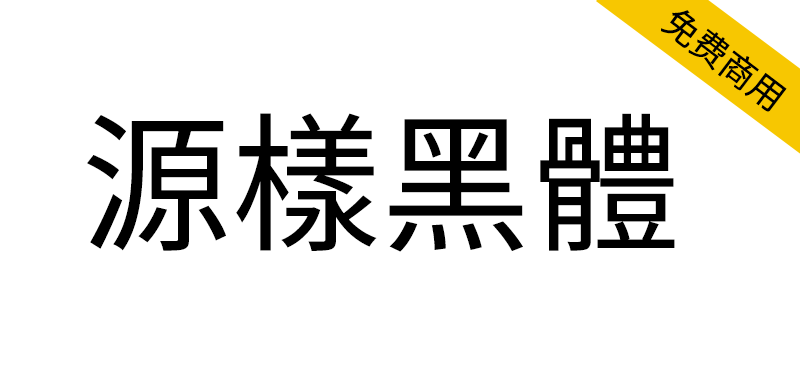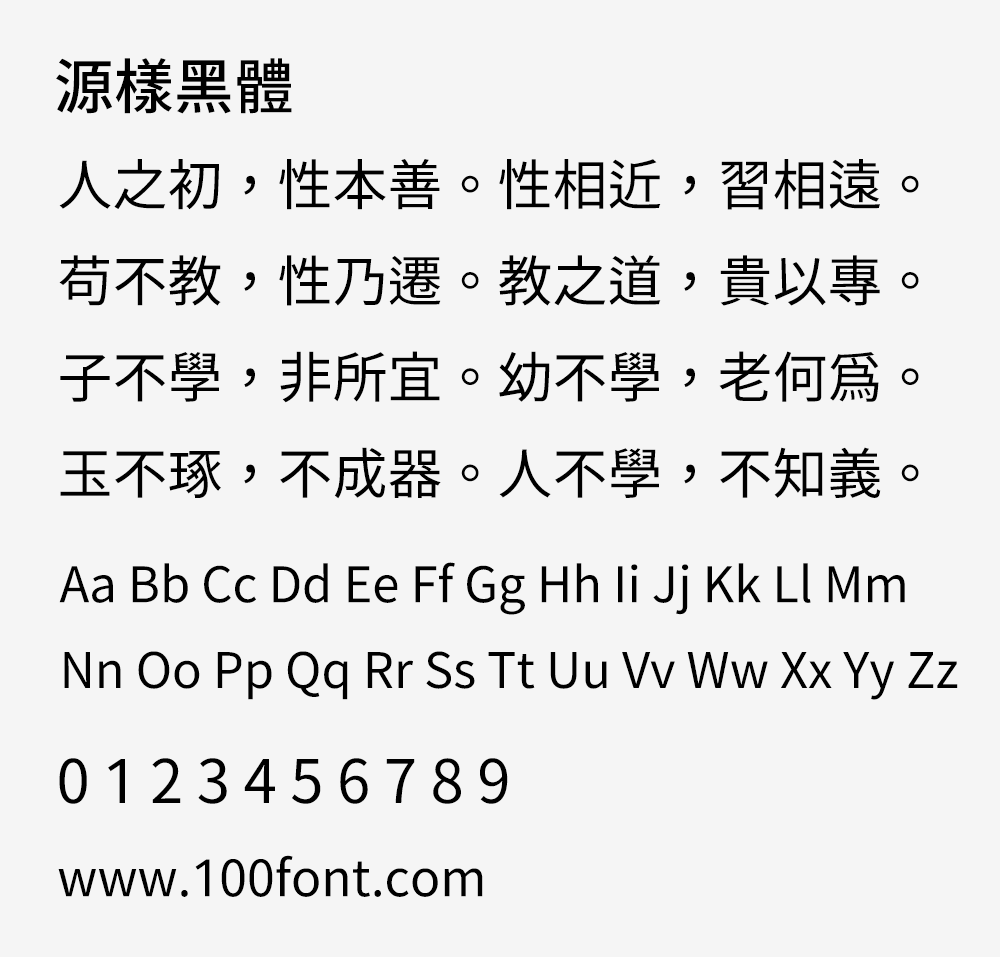
「源样黑体」是基于思源黑体的开放原始码中文字体。采用思源黑体韩文(KR)版本为主的字符,配合繁体中文惯用的置中标点,可排版传统印刷体风格的文件。
传统印刷体:思源黑体预设的台湾版本(TW)采用教育部标准字体,虽然适合教育用途,但不尽符合传统印刷体审美观。例如点、挑、撇笔画太多,文件排列时的的跳动感较大。源样黑体采用KR版本的字符为主,较接近传统印刷体习惯,排列感较为整齐。
源样黑体并没有造新的字符,所有字符都是来自思源黑体本身。所以KR版本未收录的罕用字或简体字,仍然会是TW、CN风格。
汉字不缺字:保留思源宋体所支持之所有汉字(包或日、韩文汉字与简体字),一般会用到的汉字几乎不会有缺字问题。同时也保留了所有日文假名。(但删除了高达1万字的韩文字,有效降低字体档大小。)
源样黑体并没有造新的字符,简体字等当然会是CN风格。
标点符合繁体中文习惯:直接使用思源黑体KR版本排中文,会有标点置于左下的问题。源样黑体的标点符号仍采用繁体中文习惯,逗号、句号等都置于正中央。并且系统能正确识别为繁体中文字体。
另外,思源黑体的标点符号如「,」「。」设定有比例宽度的压缩字宽,在Illustrator、InDesign等环境下预设会压缩50%显示。这往往会让标点显得过窄。源样黑体移除了部分符号的压缩字宽信息,让这些标点符号字宽原则上保持全形。
注意提醒:这款字体主要适用于繁体中文,虽然也支持简体中文、韩语、日语,但是可能会出现错别字等情况。